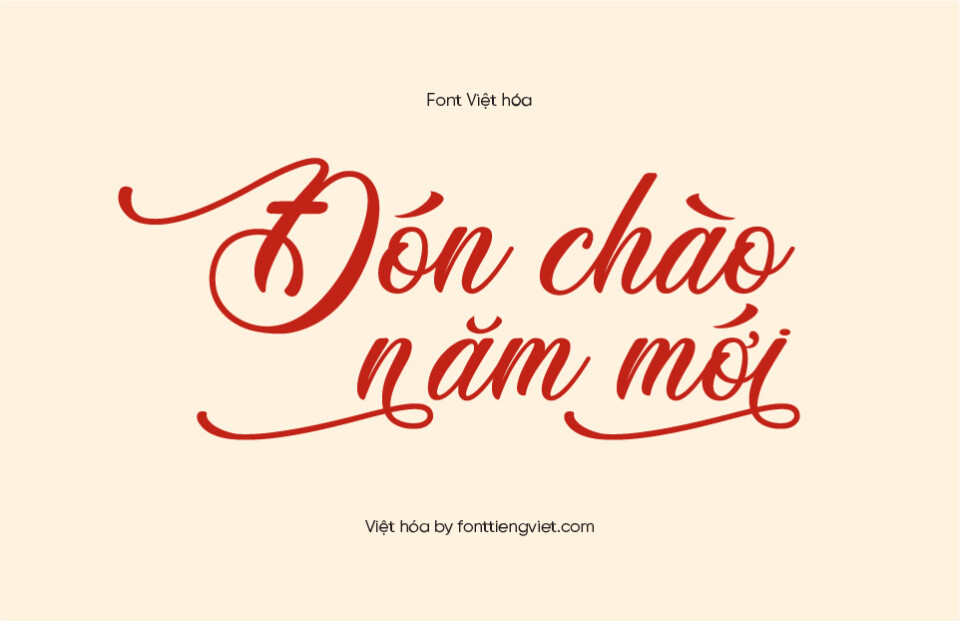
Giới thiệu bộ Font Việt hóa 1FTV VIP Weather Sunday – Tết
Chào đón không khí rộn ràng của những ngày cuối năm, bộ Font Việt hóa 1FTV VIP Weather Sunday – Tết chính thức ra mắt để phục vụ nhu cầu thiết kế sáng tạo. Đây là lựa chọn hoàn hảo cho các bạn học sinh và giáo viên khi muốn trang trí bảng tin, làm thiệp chúc mừng hay thiết kế slide bài giảng sinh động. Với phong cách thanh lịch nhưng không kém phần ấm áp, Font Chữ này giúp truyền tải trọn vẹn thông điệp yêu thương trong dịp Tết cổ truyền. Việc sử dụng các bộ phông chữ đã được bản địa hóa giúp loại bỏ hoàn toàn lỗi hiển thị dấu tiếng Việt, mang lại sự chuyên nghiệp và chỉn chu cho mọi sản phẩm đồ họa học đường.
Đặc điểm nổi bật của phông chữ
Bộ Font Việt hóa 1FTV VIP Weather Sunday – Tết sở hữu các đường nét uốn lượn mềm mại, gợi liên tưởng đến những nhành mai nhành đào đang khoe sắc. Điểm đặc biệt của nó là sự linh hoạt, phù hợp từ các tiêu đề báo tường cho đến những đoạn văn bản ngắn trên bao lì xì. Các ký tự được tinh chỉnh kỹ lưỡng, đảm bảo độ sắc nét cao khi in ấn trên nhiều chất liệu khác nhau.
Cách ứng dụng Font Việt hóa 1FTV VIP Weather Sunday – Tết hiệu quả
Để tận dụng tối đa vẻ đẹp của phông chữ này, bạn nên kết hợp với những gam màu rực rỡ như đỏ, vàng hoặc xanh lá cây. Trong môi trường sư phạm, thầy cô có thể dùng bộ chữ để làm mới các tài liệu giảng dạy, giúp học sinh hứng thú hơn với bài học về văn hóa dân tộc. Ngoài ra, việc phối hợp cùng các icon hình bánh chưng, hoa mai sẽ tạo nên một bố cục hài hòa và đậm chất nghệ thuật.
Lưu ý khi sử dụng thiết kế